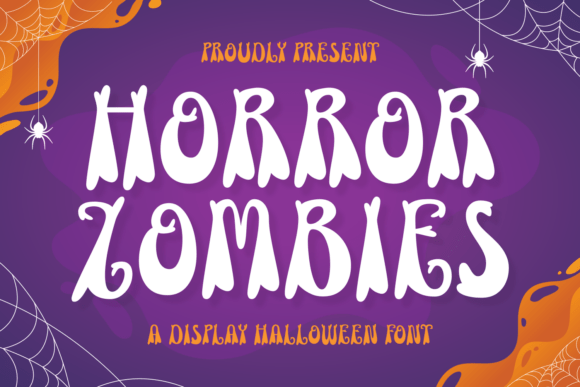
Horror Zombies
การค้นหาองค์ประกอบการออกแบบที่เหมาะสมอาจเป็นเรื่องท้าทาย แต่ Horror Zombies นำเสนอคอลเลกชันที่โดดเด่นซึ่งช่วยยกระดับงานของคุณได้ทันที
สร้างขึ้นอย่างแม่นยำ Horror Zombies ให้เวกเตอร์ที่สะอาด พิมพ์ตัวอักษรที่ราบรื่น และใบอนุญาตเชิงพาณิชย์เพื่อความสบายใจ
ไม่ว่าคุณจะสร้างผลิตภัณฑ์ POD (Print on Demand) คำเชิญงานแต่งงาน หรือกราฟิกโซเชียลมีเดีย Horror Zombies ก็เหมาะสมอย่างยิ่ง